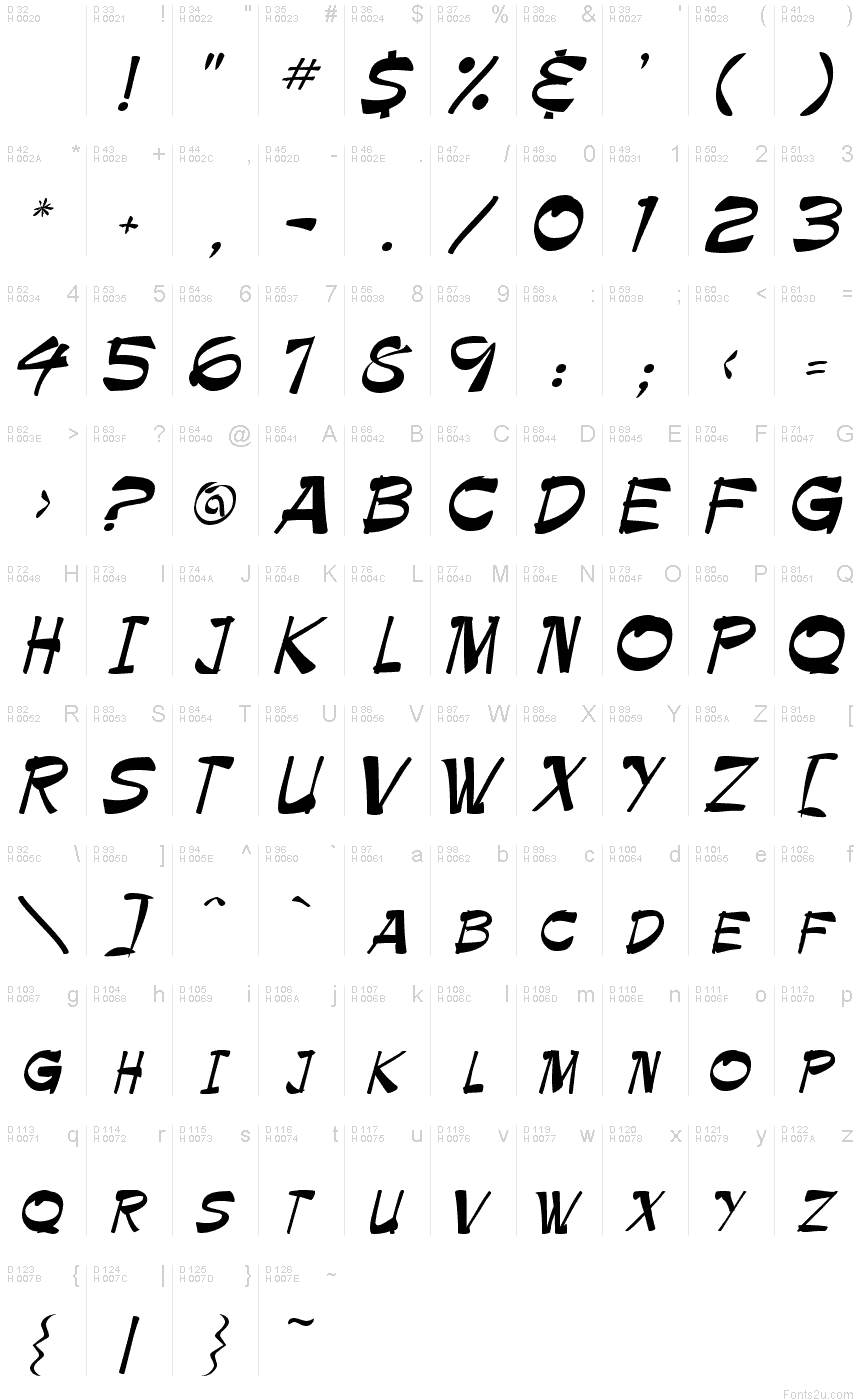
Ballot 是一款免费的毛笔风格展示字体,充满大胆而张扬的手工感。字符仿佛是用浓墨重彩的粗头马克笔一气呵成,略带倾斜、不规则且动感十足,巨大的涡旋笔画更增添了一抹俏皮的涂鸦风格。它给人一种即兴而张扬的感觉,仿佛每个字都是在页面上呼喊而出,而非静止陈列。
使用 Ballot,您的标题将瞬间获得那种让人无法忽视的街头海报感。这款免费字体非常适合活动传单、独立杂志、音乐封面、抗议海报、儿童读物标题,以及那些需要展现真实、粗犷感的品牌设计。记得放大字号,留足呼吸空间,并搭配一款干净的无衬线字体作为正文,让 Ballot 粗犷的笔触成为全场焦点。